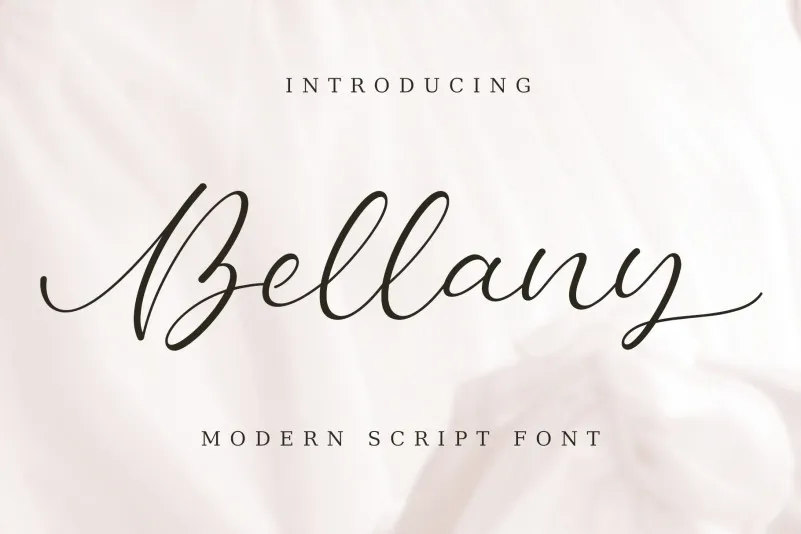
Bellany – Modern Script Font – Download Grátis
A Bellany – Modern Script Font é uma escolha perfeita para designers apaixonados por letras elegantes e modernas. Este moderno e sofisticado tipo de letra foi criado pela AVType designer e agora está disponível através de Befonts, oferecendo um amplo espectro de possibilidades para estilos formais e branding. Esse font é ideal para incorporar em designs como logotipos boutique, cartões de visita, convites de casamento, revistas, pôsteres de moda, catálogos de moda, frases motivacionais, logos, redes sociais, capas de livros e muito mais. Com sua natureza elegante e moderna, a Bellany proporcionará um toque refinado aos seus projetos, ajudando-o a destacar-se em uma variedade de usos. Nesta categoria de fonts Script, ela se destaca como o tipo certo para quem busca expressar elegância contemporânea em cada projeto gráfico.